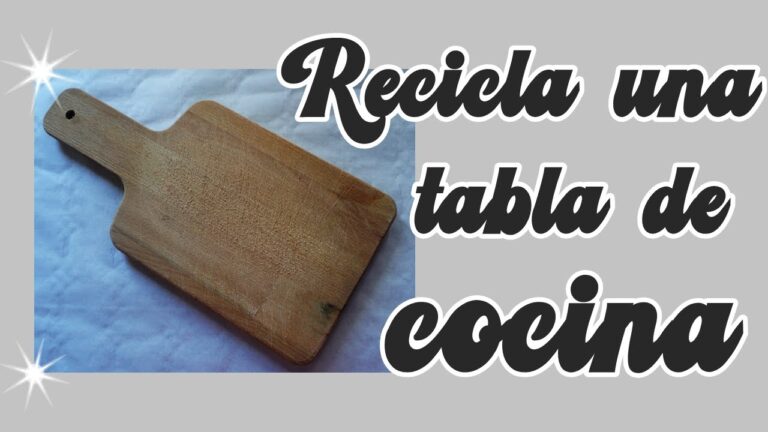
Encanto Vintage: La Magia de la Tipografía Retro
El encanto del estilo vintage en tipografía ha resurgido con fuerza en el diseño contemporáneo, capturando la esencia de épocas pasadas y fusionándola con la modernidad. Este enfoque nostálgico no solo evoca recuerdos y emociones, sino que también añade una estética única a proyectos creativos. Desde carteles hasta logotipos, la tipografía vintage se convierte en un puente entre el ayer y el hoy, atrayendo a aquellos que buscan autenticidad y carácter en un mundo cada vez más digital. En este artículo, exploraremos cómo este estilo atemporal sigue influenciando las tendencias actuales y su relevancia en el diseño gráfico moderno.
¿Cuál es el nombre de la fuente tipográfica vintage?
Las tipografías vintage evocan una estética nostálgica que rinde homenaje a los métodos artísticos de épocas pasadas. Inspiradas en el arte manual de la era dorada del diseño gráfico, estas fuentes reflejan la meticulosidad y el encanto de un tiempo en el que cada trazo era cuidadosamente elaborado a mano. Este estilo no solo añade un toque de elegancia, sino que también cuenta historias de creatividad y dedicación.
Al elegir una fuente vintage, se opta por un elemento visual que trasciende el tiempo y conecta con la tradición del diseño. Estas tipografías son perfectas para proyectos que buscan transmitir autenticidad y un sentido de historia, ya sea en branding, carteles o publicaciones. Su presencia aporta carácter y un aire distintivo que capta la atención y resalta el mensaje de manera productiva.
¿Cuál es el nombre de la tipografía de encanto?
La tipografía de Encanto ha capturado la atención de muchos, convirtiéndose en una de las más populares en las últimas semanas. Su estilo único y encantador refleja la magia de la película, lo que la hace ideal para proyectos creativos, desde invitaciones hasta publicaciones en redes sociales. La búsqueda de esta fuente ha crecido exponencialmente, demostrando el impacto que la estética de Encanto ha tenido en la cultura visual actual.
Para aquellos que desean incorporar este hermoso estilo en sus trabajos, la solución es sencilla. La fuente Madrigal Font es la opción perfecta para quienes quieren resaltar la esencia mágica de Encanto en sus diseños. Al ser fácilmente accesible en internet, cualquier persona puede descargarla y comenzar a utilizarla en sus proyectos.
¿Qué comunican las tipografías retro?
Las tipografías retro han resurgido con fuerza en el diseño contemporáneo, brindando un aire nostálgico y auténtico a diversas creaciones visuales. Este estilo evoca un encanto vintage que nos conecta con épocas pasadas, llenas de carácter y personalidad. Al incorporar estas fuentes, los diseñadores no solo atraen la atención del espectador, sino que también transmiten una historia y una sensación de calidez que resuena en la memoria colectiva.
Reviviendo el Estilo: Tipografía que Encanta
La tipografía es mucho más que simples letras en una página; es un arte que puede transformar la estética de cualquier diseño. Al elegir una tipografía adecuada, se puede evocar una variedad de emociones y crear una conexión instantánea con el público. Desde las elegantes serifas que transmiten tradición y sofisticación, hasta las modernas sans serif que ofrecen un aire de frescura y minimalismo, cada estilo tipográfico cuenta una historia única que resuena con la identidad de la marca.
Reviviendo el estilo clásico con un toque contemporáneo, la tipografía se convierte en una herramienta poderosa para captar la atención y comunicar mensajes de manera productiva. La combinación de diferentes fuentes, tamaños y colores puede llevar a la creación de composiciones visuales impactantes que invitan a los espectadores a involucrarse. En un mundo donde la primera impresión es vital, invertir en una tipografía que encante no solo mejora la presentación, sino que también establece un vínculo duradero con la audiencia.
Letras que Cuentan Historias: El Encanto del Pasado
Las letras que han perdurado a lo largo del tiempo son testigos de historias fascinantes y profundas, que nos conectan con épocas pasadas. Cada palabra, cuidadosamente elegida, evoca emociones y recuerdos, transportándonos a momentos que definieron culturas y generaciones. En un mundo donde lo efímero reina, el poder de una buena narrativa se convierte en un refugio, recordándonos la importancia de nuestras raíces y el legado que compartimos.